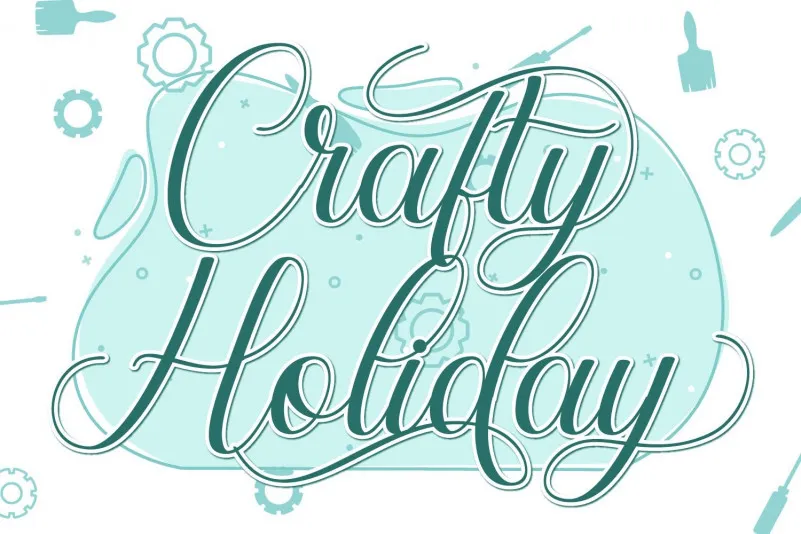
Esta fonte ‘Crafty Holiday Font’ é uma tipografia suave e fresca, ideal para designers que buscam uma mistura única de elegância moderna e autenticidade humana. Criada pelo font designer fiqiart09, essa font tem um estilo bem-humorado e cuidadosamente escrita que transmite classe e sofisticação. Perfeita tanto para criações profissionais quanto para ideias criativas, esta font é perfeitamente adaptável a uma ampla gama de aplicações. Seja para design de logotipos, rótulos de marca, cartões de convite ou materiais de decoração, este tipo de font irá destacar seus projetos e garantir que eles tenham um ar autêntico e moderno. Se você está à procura de uma fonte que combine facilidade com elegância, não pode fazer melhor do que a ‘Crafty Holiday Font’. Seja para sua próxima campanha social, projeto de evento ou design de newsletter, esta font será o elemento perfeito que dará um toque único e divertido aos seus trabalhos.